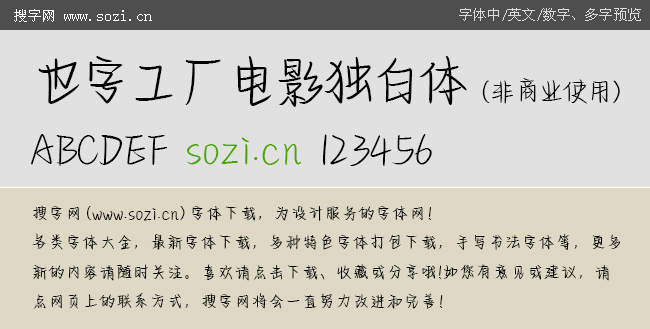
也字工廠電影獨白體
搜字網(wǎng)給大家提供一款也字工廠電影獨白體(非商業(yè)使用)中文字體下載,也字工廠電影獨白體是一款手寫書法字體,字體書寫流暢自然,字形瀟灑大方。具有很好的視覺效果。適合應(yīng)用于藝術(shù)設(shè)計、平面宣傳設(shè)計、網(wǎng)頁設(shè)計、海報設(shè)計等應(yīng)用(此字體為個人非商用版,商用可以聯(lián)系:官方網(wǎng)址:https://yefont.com/home,聯(lián)系方式:13798980448)。